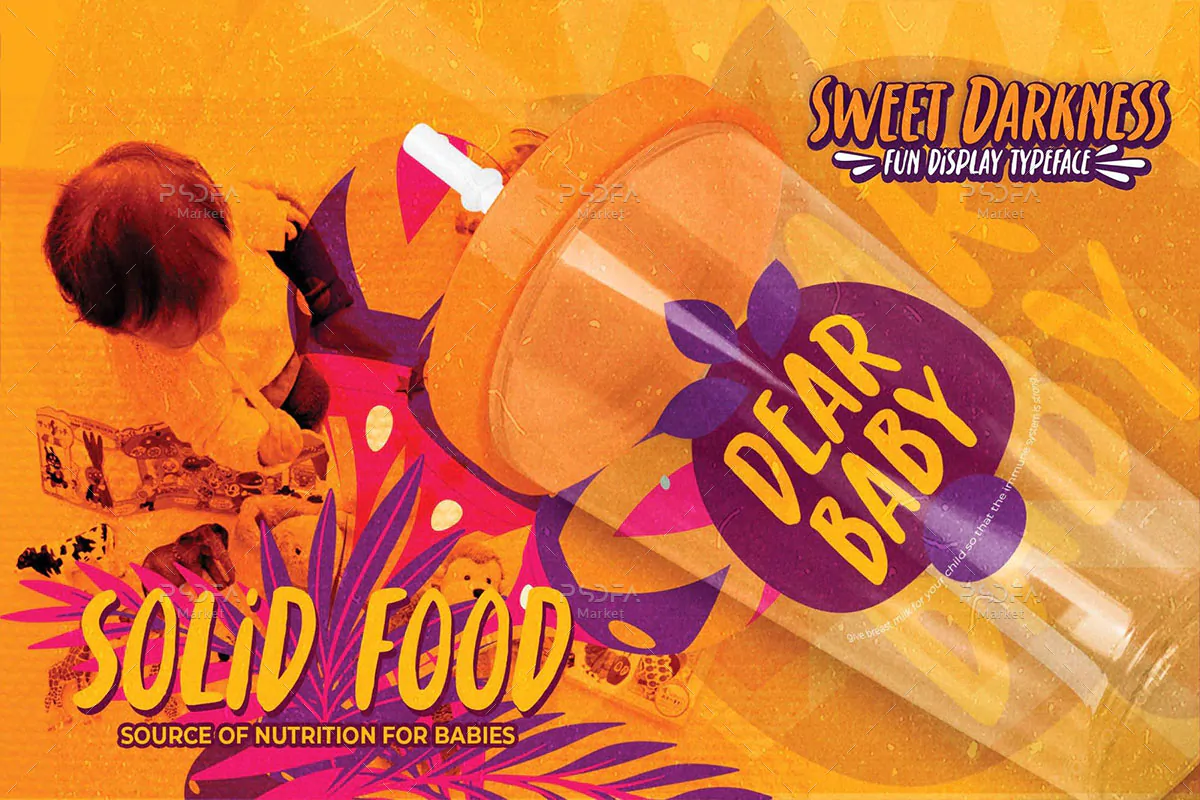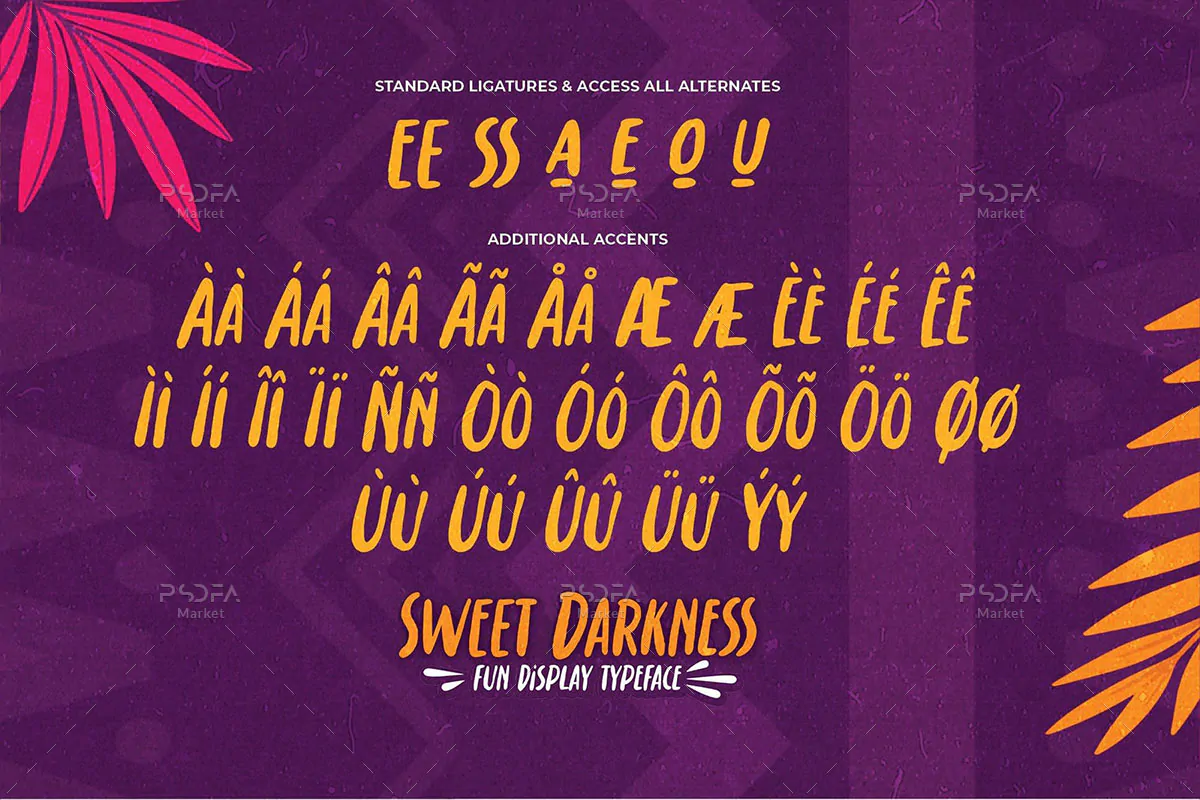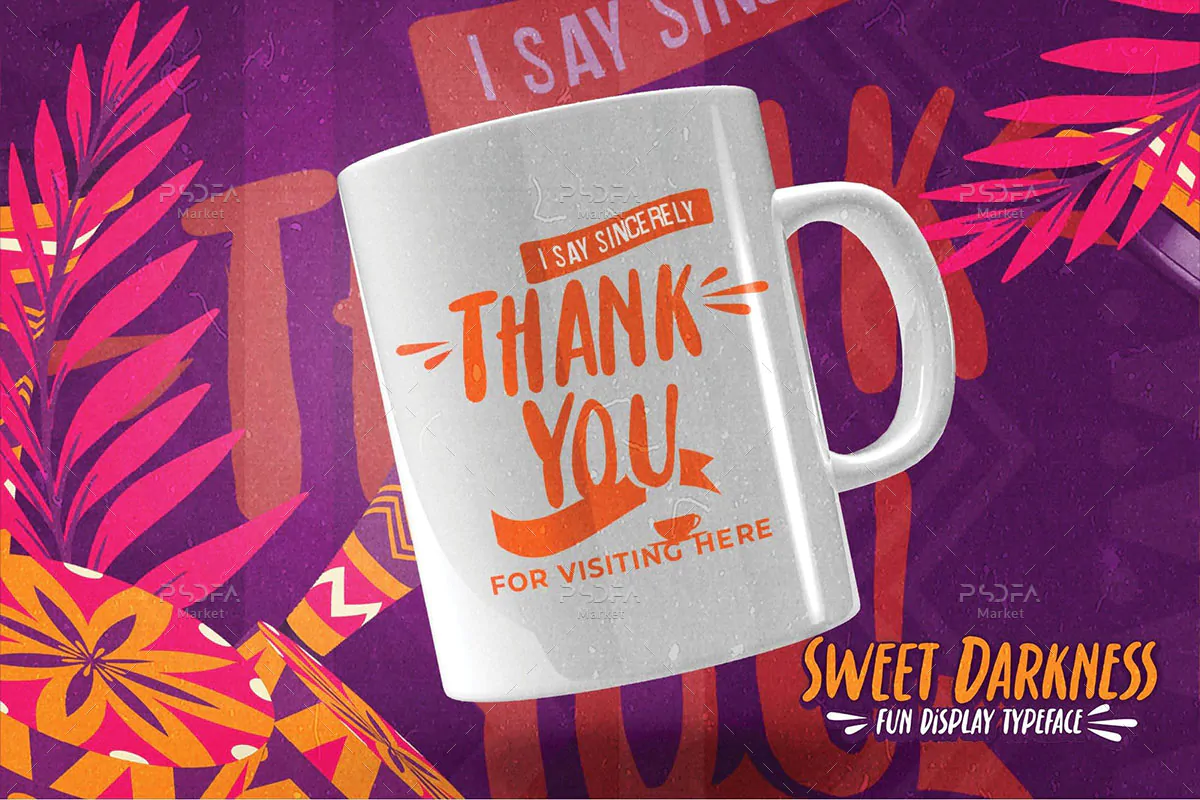
فونت فان و دراماتیک Sweet Darkness
فونت فان و دراماتیک انگلیسی
فونت فان و دراماتیک Sweet Darkness یک قلم نمایشی انگلیسی جذاب و سرگرم کننده است که مناسب جهت استفاده در طرح و پروژههای گرافیکی مختلف میباشد. فونت Sweet Darkness با وزن معمولی طراحی شده است که میتوانید از آن در طراحی پوستر، طرحهای کودکانه، تقویم، بسته بندی محصولات، ماگ و ظروف یکبار مصرف، تیشرت و … استفاده کنید.